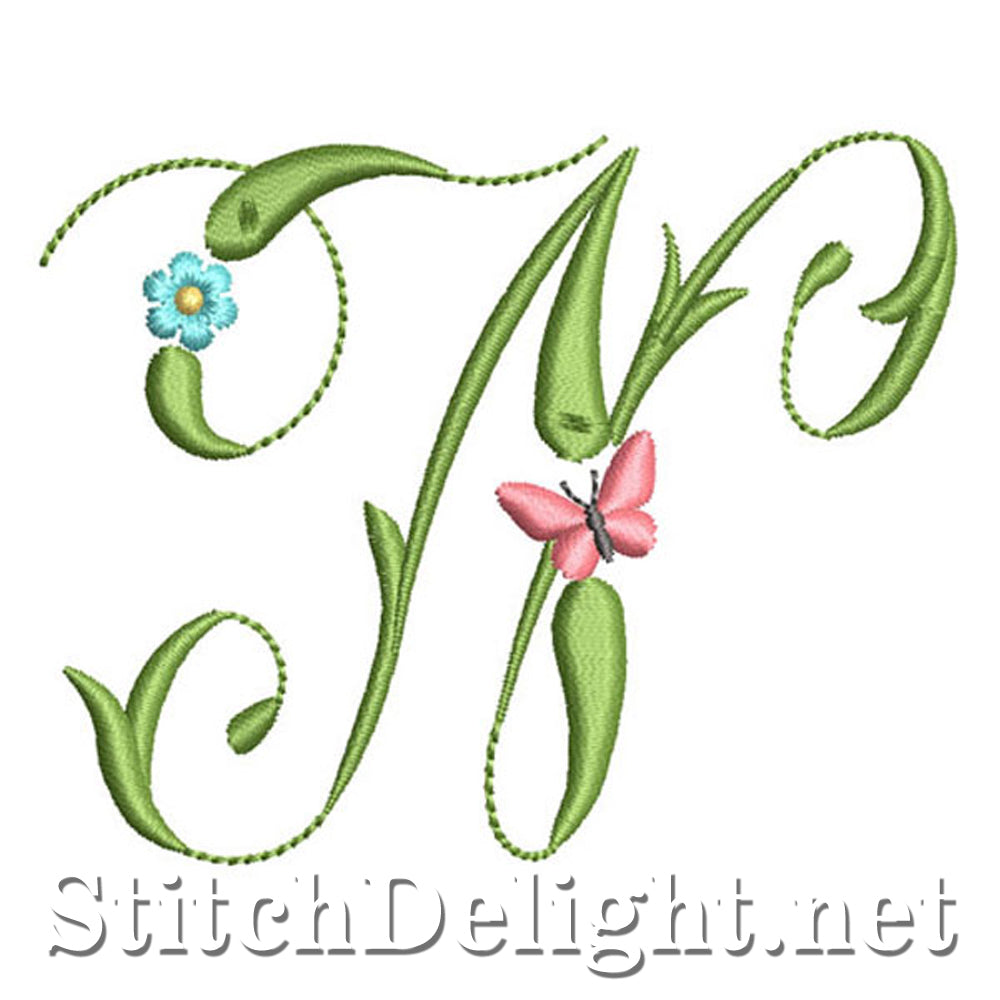
SDS1152 Papillons et Fleurs Police N
Belle police avec des fleurs et des papillons délicats - La hauteur des lettres de ces lettres est de 67 mm / 2,65"